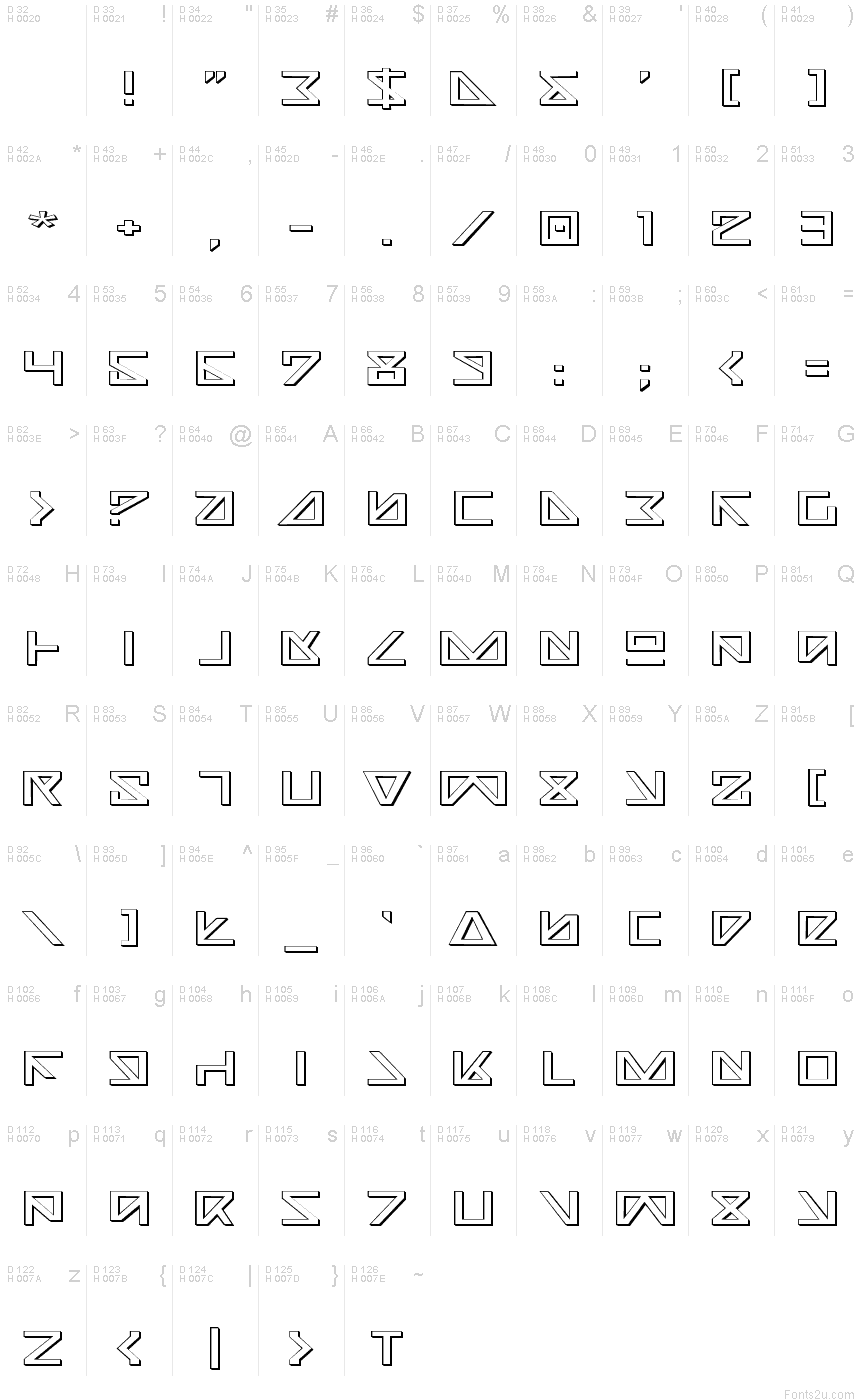
Nick Turbo Expanded 3D od Iconian Fonts to darmowy, techniczny krój pisma typu display, wyróżniający się ostrymi, kanciastymi sylwetkami, długimi diagonalnymi cięciami i spójnym, wyciągniętym profilem bocznym, który nadaje każdej literze głębię w stylu maszyn arcade. Konturowa konstrukcja sprawia, że efekt trójwymiarowości jest lekki, a nie przytłaczający, podczas gdy powtarzające się kąty nadają literom szybki, schematyczny i precyzyjnie zaprojektowany charakter.
To połączenie sprawdza się w tytułach gier, grafikach e-sportowych, plakatach science-fiction, nakładkach na streamy i okładkach albumów, gdzie krótkie hasła potrzebują wyraźnego, cyfrowego akcentu. Krój może również stanowić podstawę logotypów lub opakowań dla gadżetów i napojów energetycznych, ponieważ wycięte narożniki i przesunięta głębia tworzą mechaniczny rytm, który bardziej przypomina projektowany sprzęt niż zwykłe napisy displayowe.
Nick Turbo Expanded 3D